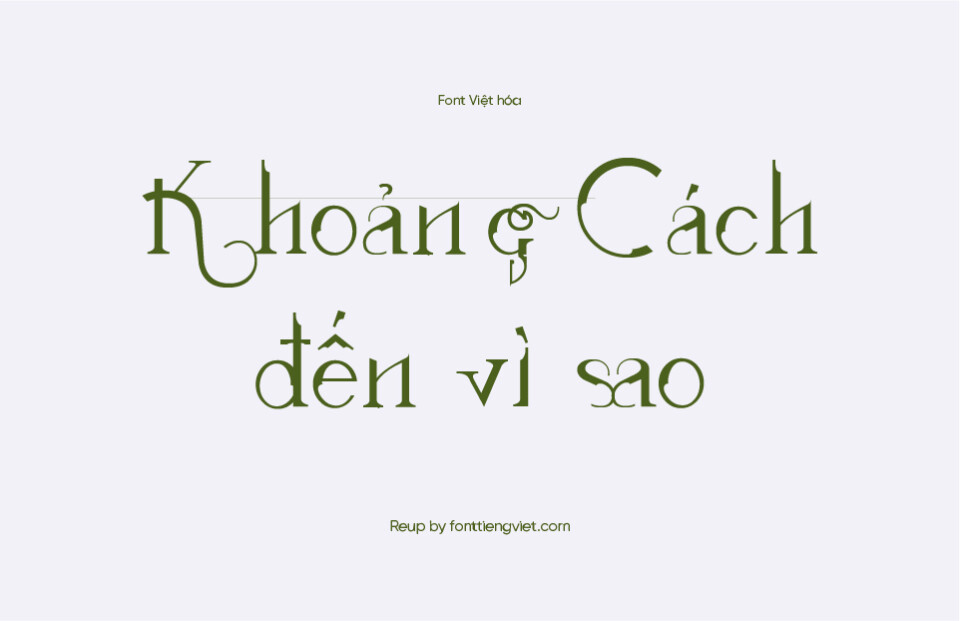
Font Việt hóa UVF Rapture Heavenly
Giới thiệu về Font Việt hóa UVF Rapture Heavenly
Trong thế giới thiết kế đồ họa hiện đại, việc lựa chọn một bộ Font Miễn Phí chất lượng luôn là ưu tiên hàng đầu của các nhà sáng tạo. Font Việt hóa UVF Rapture Heavenly nổi lên như một lựa chọn hoàn hảo nhờ sự kết hợp tinh tế giữa nét chữ thanh thoát và phong cách nghệ thuật độc đáo. Đây là bộ phông chữ được tinh chỉnh kỹ lưỡng để phù hợp hoàn toàn với bảng mã tiếng Việt, giúp người dùng không còn lo lắng về lỗi hiển thị dấu hay khoảng cách ký tự không đều.
Đặc điểm nổi bật của phông chữ
Bộ Font Việt hóa UVF Rapture Heavenly sở hữu các đường nét uốn lượn mềm mại, mang lại cảm giác sang trọng và bay bổng đúng như tên gọi “Heavenly” của nó. Các ký tự được thiết kế với độ tương phản cao, tạo nên điểm nhấn thị giác mạnh mẽ cho mọi bản thiết kế từ bìa sách, thiệp mời đến các biểu ngữ trang trí trong nhà trường.
Ứng dụng thực tế của Font Việt hóa UVF Rapture Heavenly
Nhờ tính thẩm mỹ cao, bộ phông này thường xuyên xuất hiện trong các dự án thiết kế thương hiệu và truyền thông. Đối với các bạn học sinh và giáo viên, việc sử dụng Font Việt hóa UVF Rapture Heavenly trong các bài thuyết trình hay thiết kế báo tường sẽ giúp nội dung trở nên sinh động và chuyên nghiệp hơn rất nhiều.
Lưu ý khi sử dụng trong thiết kế
Khi làm việc với Font Việt hóa UVF Rapture Heavenly, bạn nên kết hợp với các phông chữ không chân (sans-serif) đơn giản để cân bằng bố cục. Điều này giúp thông tin chính được nổi bật mà vẫn giữ được sự hài hòa tổng thể cho tác phẩm đồ họa của bạn.